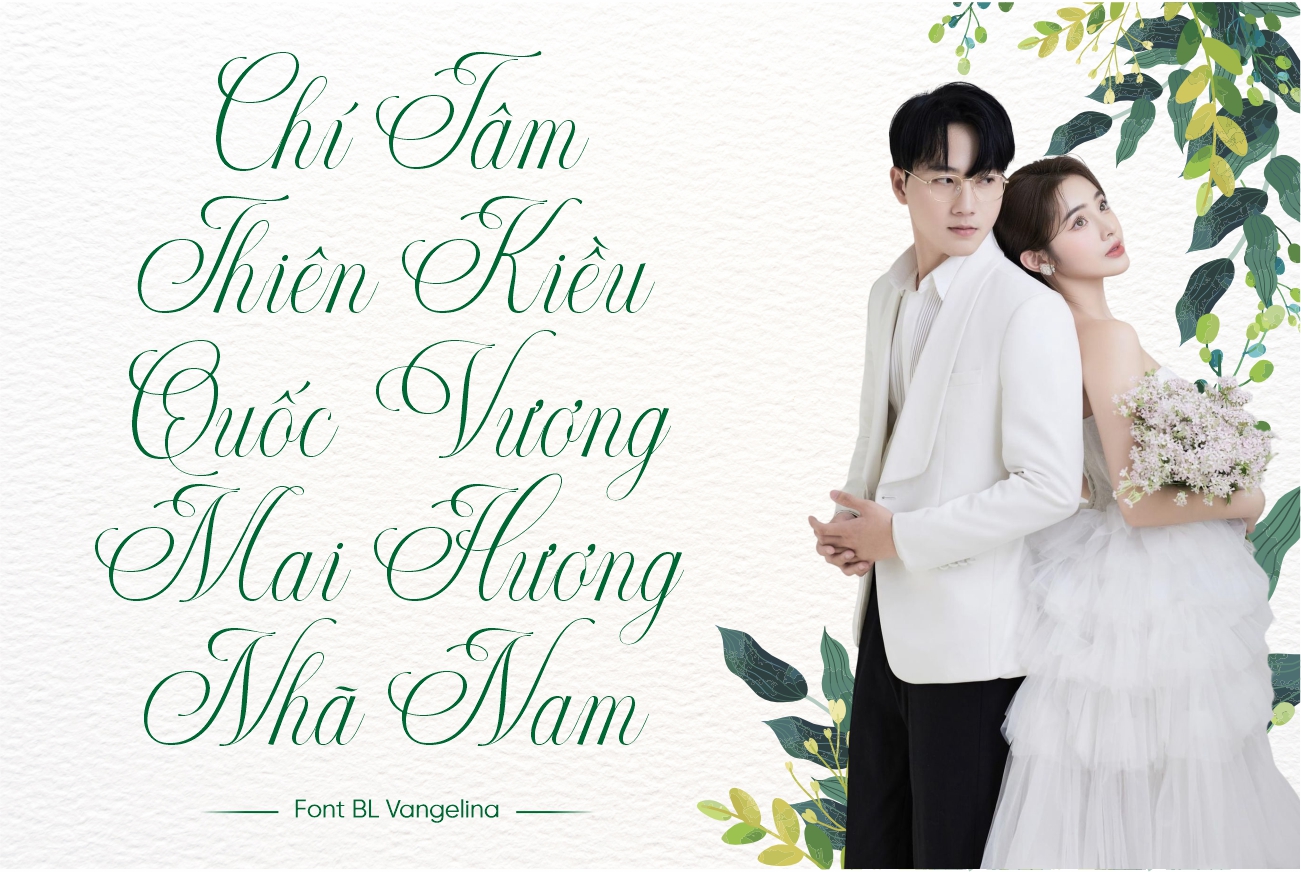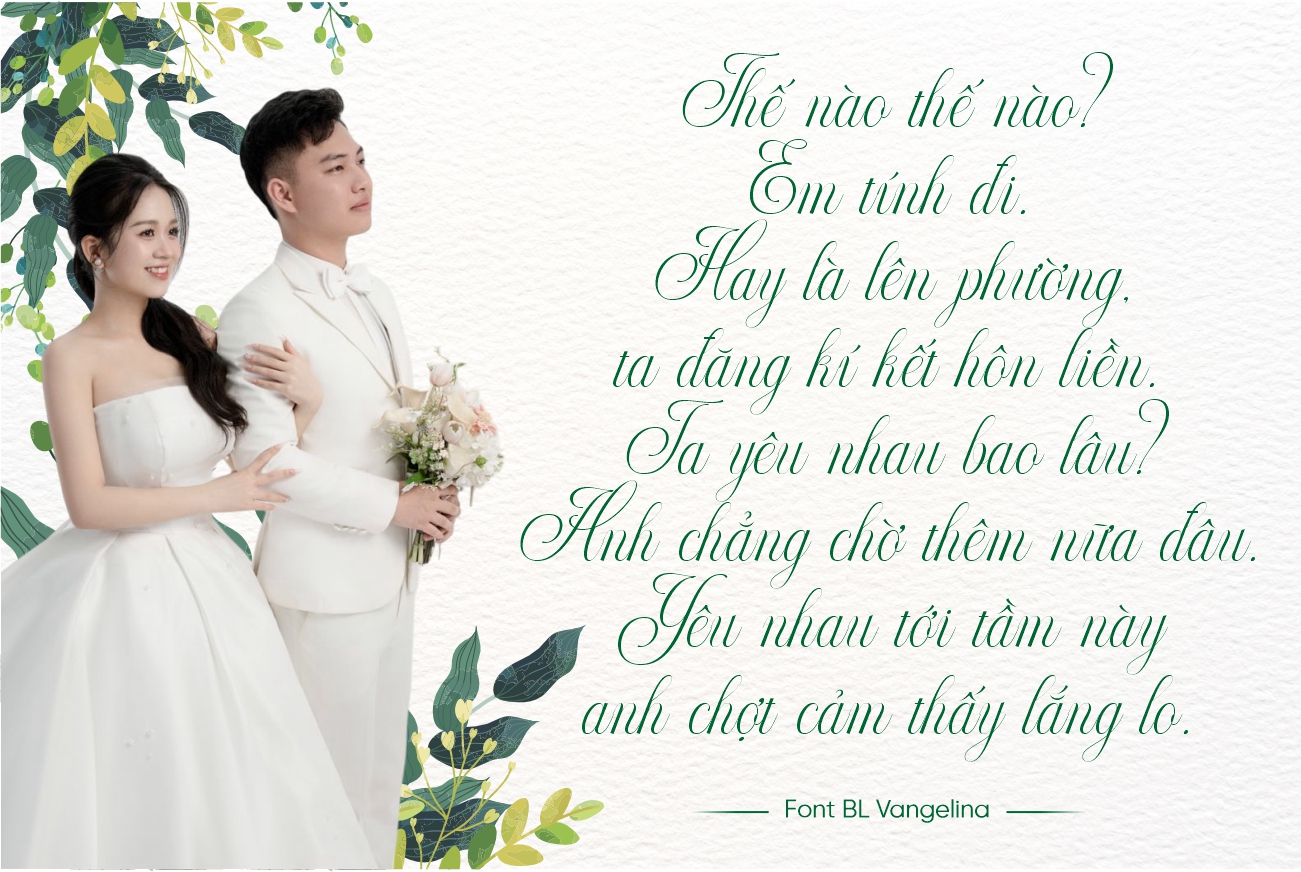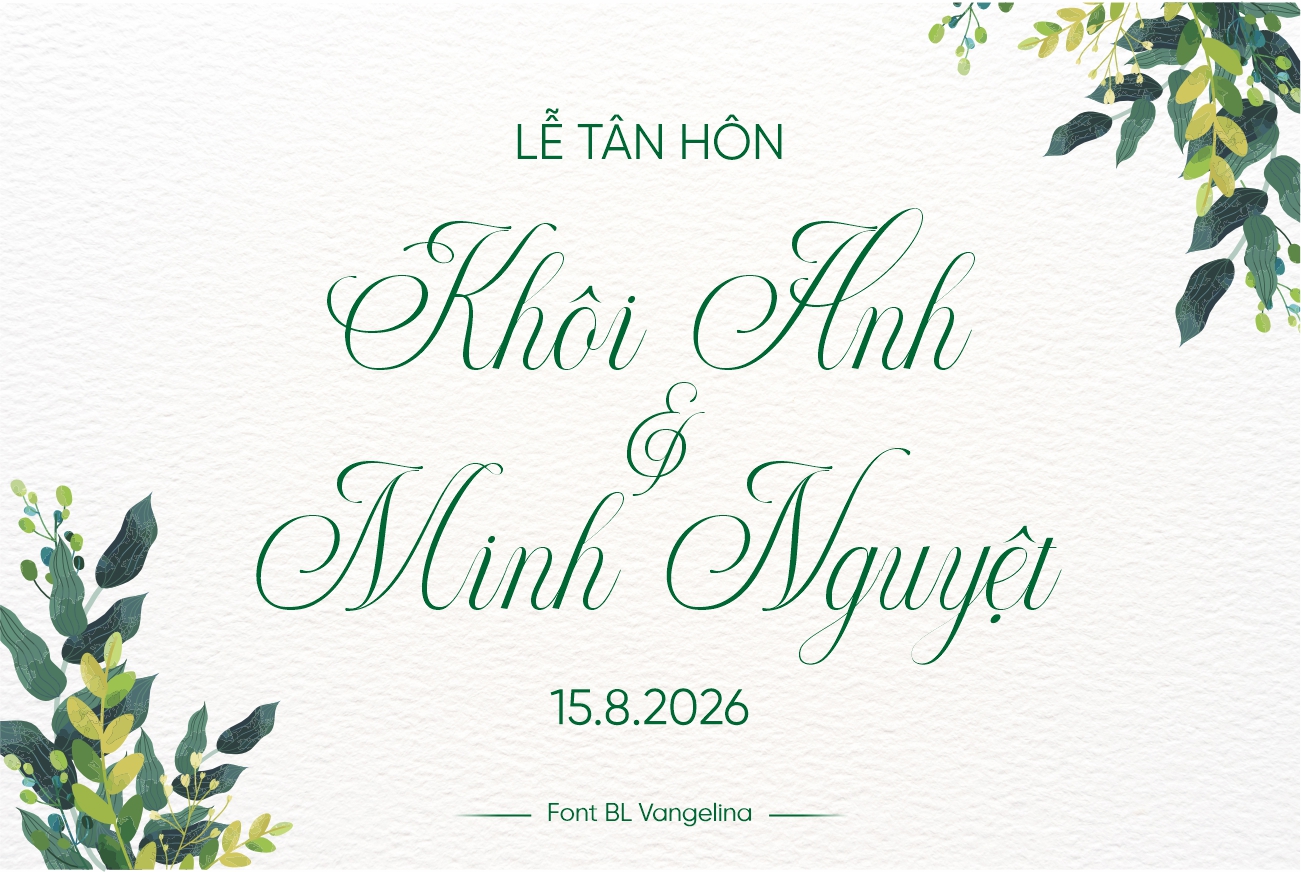
BL Vangelina - Font thiệp cưới hiện đại và tinh tế
BL Vangelina là phiên bản Việt hóa của font chữ Vangelina do Pixesia Studio thiết kế, được Team BL tinh chỉnh để phù hợp hoàn toàn với tiếng Việt. Font nguyên bản mang tinh thần nhẹ nhàng, nữ tính và giàu tính trang trí, lấy cảm hứng từ chữ viết tay kết hợp thư pháp hiện đại. Khi được Việt hóa, BL Vangelina vẫn giữ trọn vẻ đẹp nguyên bản, đồng thời bổ sung hệ thống dấu và ký tự đầy đủ, giúp người dùng yên tâm ứng dụng trong nhiều ấn phẩm thiết kế, đặc biệt là các sản phẩm mang tính kỷ niệm và cảm xúc cao như font thiệp cưới.
Về kiểu dáng, BL Vangelina thể hiện rõ nét một kiểu chữ hiện đại, duyên dáng và tinh tế. Các ký tự có độ cong mềm vừa phải, nét chữ thanh thoát nhưng không mảnh yếu, tạo cảm giác sang trọng và dễ đọc. Điểm nhấn của font nằm ở các nét trang trí phong cách tạo cảm giác vẻ đẹp vượt thời gian, được đặt khéo léo ở đầu và cuối nét chữ, giúp tổng thể trở nên cuốn hút mà không gây rối mắt. Sự trau chuốt trong từng chi tiết khiến font mang dáng vẻ cao cấp, phù hợp với các thiết kế cần sự tinh tế và chỉn chu.
Trong ứng dụng thực tế, BL Vangelina phát huy tối đa giá trị thẩm mỹ khi sử dụng cho font thiệp cưới, thiệp mời, thiệp báo hỷ, menu tiệc cưới hoặc các ấn phẩm in ấn cao cấp. Nhờ cấu trúc chữ rõ ràng và nhịp điệu thị giác hài hòa, font có thể kết hợp tốt với các kiểu chữ serif hoặc sans serif đơn giản để tạo bố cục cân đối. Đặc biệt, BL Vangelina mang đến sự cân đối tinh tế giữa nét quyến rũ cổ điển và phong cách hiện đại, giúp thiết kế vừa lãng mạn vừa hợp xu hướng, không bị lỗi thời theo thời gian.
Xét về nguồn gốc, Vangelina là sản phẩm tiêu biểu cho phong cách thiết kế mềm mại và tinh xảo của Pixesia Studio, nơi đề cao cảm xúc và tính thẩm mỹ lâu dài. Qua quá trình Việt hóa, Team BL đã điều chỉnh lại tỷ lệ, khoảng cách chữ và dấu để đảm bảo sự mượt mà khi sử dụng tiếng Việt, đồng thời giữ nguyên tinh thần nguyên bản của font. Với sự hòa quyện giữa truyền thống và hiện đại, BL Vangelina trở thành lựa chọn lý tưởng cho những ai đang tìm kiếm một kiểu chữ hiện đại, duyên dáng và tinh tế, đủ sang trọng cho các thiết kế cưới và đủ linh hoạt cho nhiều ấn phẩm sáng tạo mang dấu ấn cá nhân.